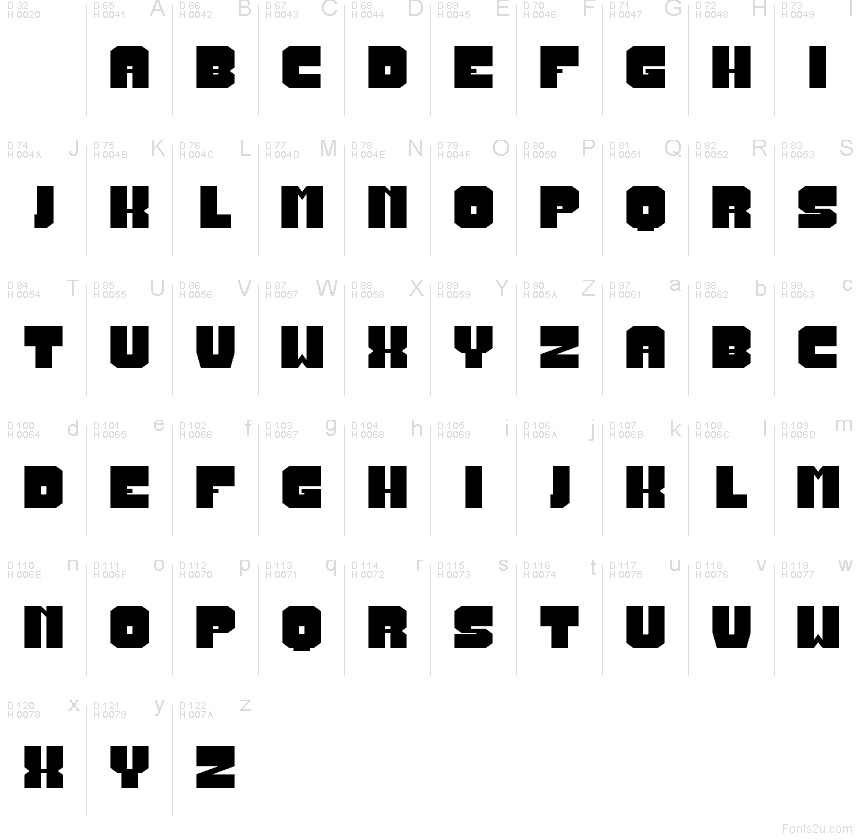
Computer Desktop od Vladimira Nikolica je bezplatné techno display písmo postavené z masívnych geometrických kapitálok. Štvorcové rámy, skosené rohy a úzke obdĺžnikové otvory dodávajú písmenám vzhľad strojovo rezaných panelov. Silueta je strohá a kompaktná.
Schémy obvodov, herné rozhrania a ostro rezané geometrické ilustrácie zdieľajú jeho modulárnu konštrukciu, vďaka čomu sa písmo skvele hodí na sci-fi plagáty, hernú grafiku a obaly elektronickej hudby. V redakčnom dizajne dokáže premeniť názov technologického článku na súčasť motívu rozhrania stránky, pričom tvary písmen pôsobia skôr ako ovládacie prvky alebo komponenty než ako obyčajný text.